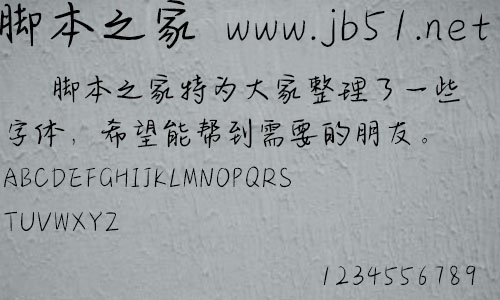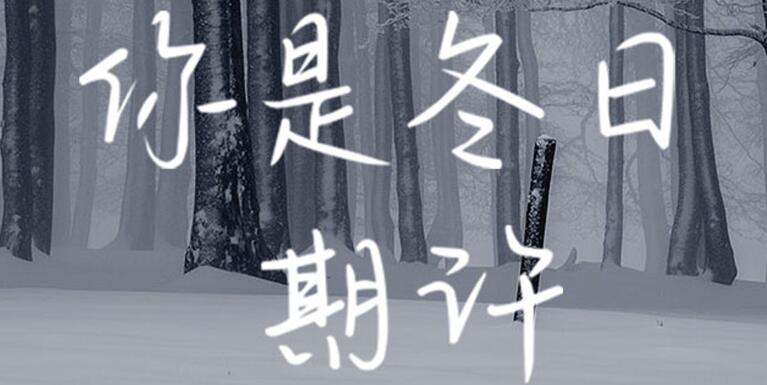
方正手跡-你是冬日期許由方正字庫(kù)王航設(shè)計(jì)師出品的藝術(shù)字體,該字體筆畫(huà)流暢舒展,部分筆畫(huà)拉出銳利筆鋒,適合應(yīng)用于藝術(shù)設(shè)計(jì)、平面宣傳設(shè)計(jì)、網(wǎng)頁(yè)設(shè)計(jì),書(shū)法等領(lǐng)域。
你是冬日期許這款字結(jié)構(gòu)緊湊,筆畫(huà)流暢舒展,部分筆畫(huà)拉出銳利筆鋒,使得字體瀟灑優(yōu)雅的同時(shí)不失風(fēng)骨。該字體適用于文藝類的書(shū)刊、品牌廣告和產(chǎn)品包裝設(shè)計(jì),以及社交網(wǎng)絡(luò)的個(gè)性化用字。。